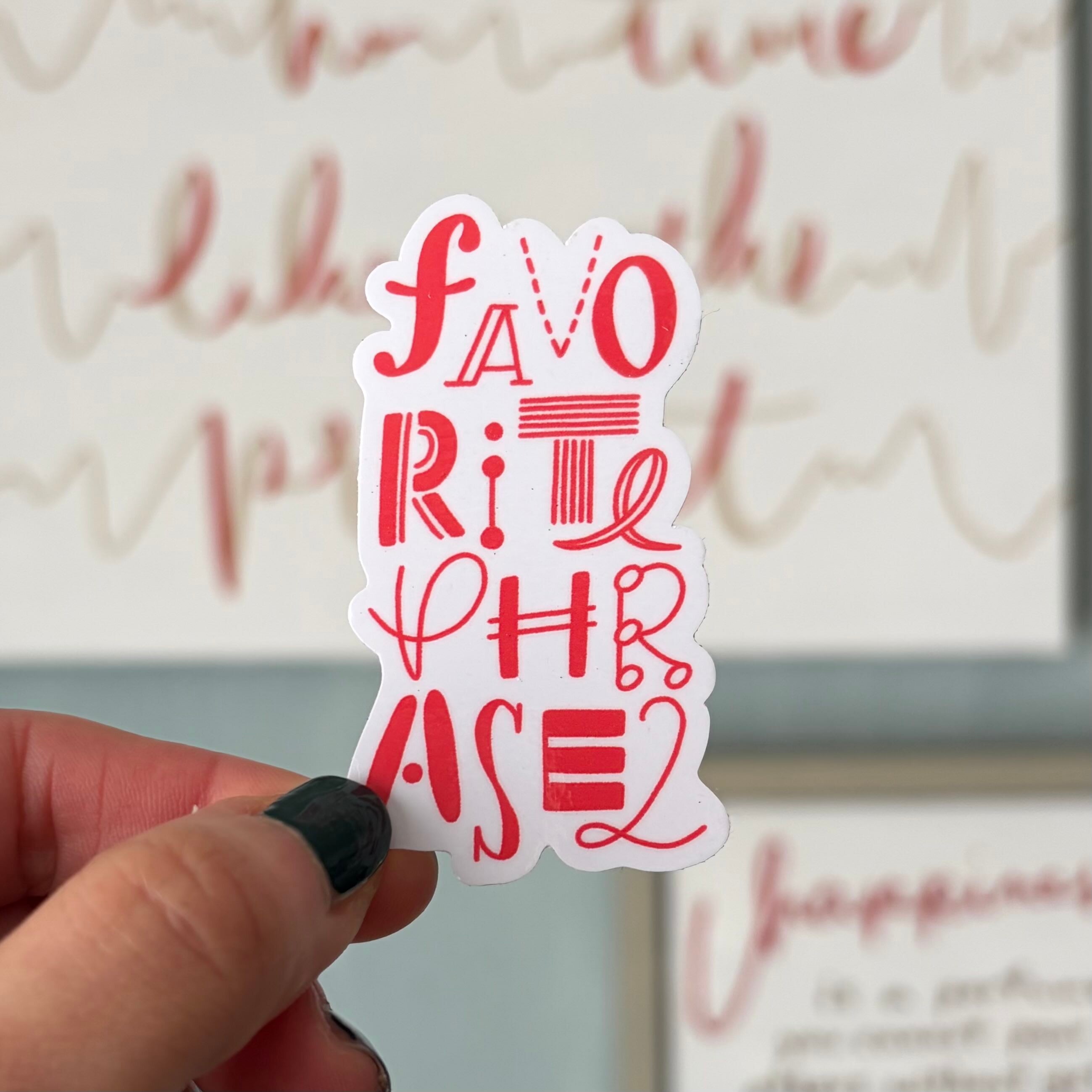
FAVORITE PHRASE2 文字ステッカー
2026年個展「FAVORITE PHRASE2」メインビジュアルのステッカー。
PHRASEは「言葉のフレーズ」以外に「音楽のフレーズ/旋律」の意味でもあります。
全フォント、音楽と楽譜をモチーフにしたものになっています。
音楽やってる方、ぜひ答え合わせしてみてください♪